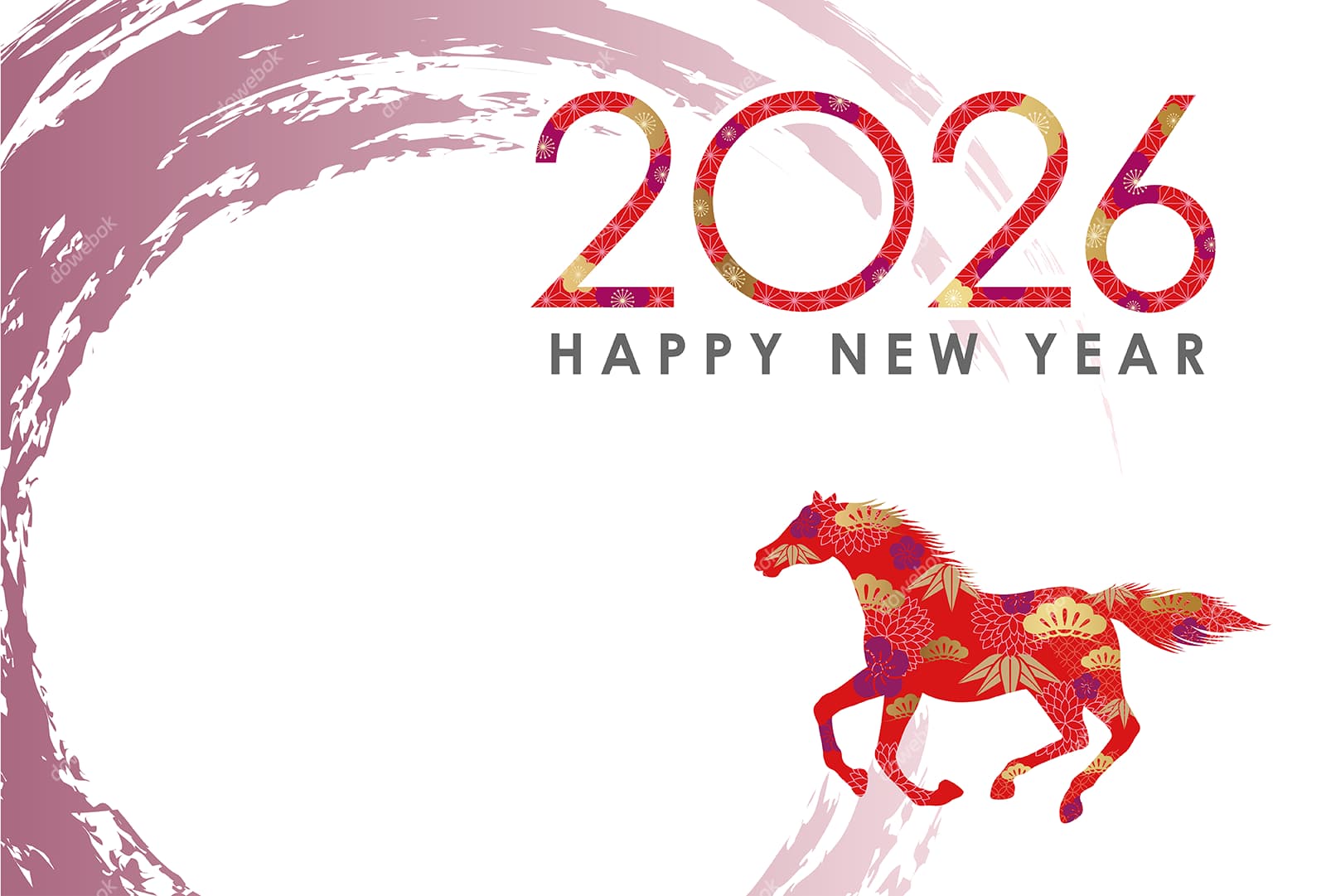
这是一款奔腾的花饰骏马 2026 新年快乐矢量素材,纯白背景左侧衬着淡紫笔触纹理,“2026” 以彩金花卉纹样呈现,醒目鲜活。下方 “Happy New Year” 字样简约呼应,右侧奔腾的花饰骏马契合马年生肖,纹样与数字风格统一。整体以笔触肌理 + 彩金元素,既显新春的雅致格调,又借生肖马传递节日吉意,灵动中透出浓郁的年节氛围。